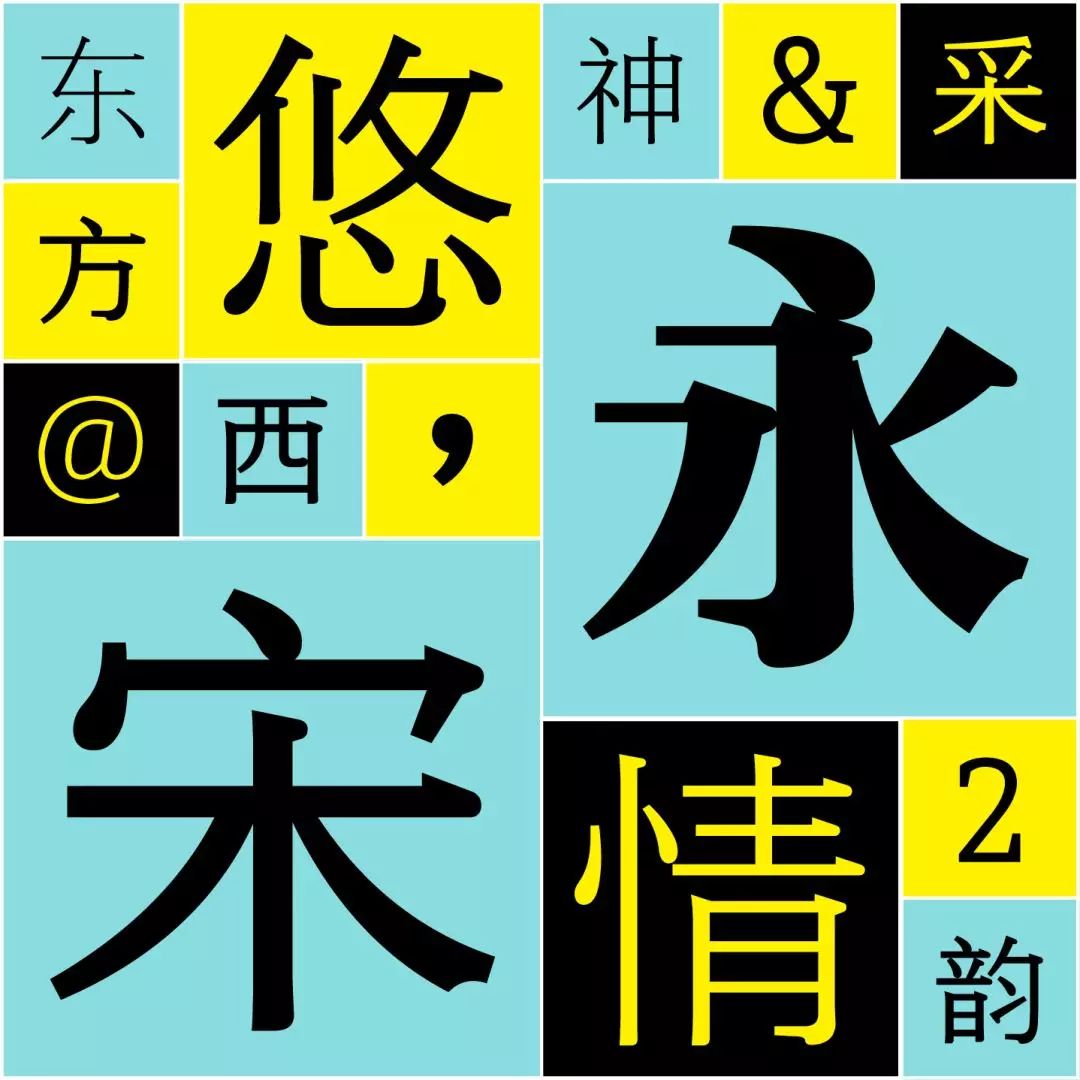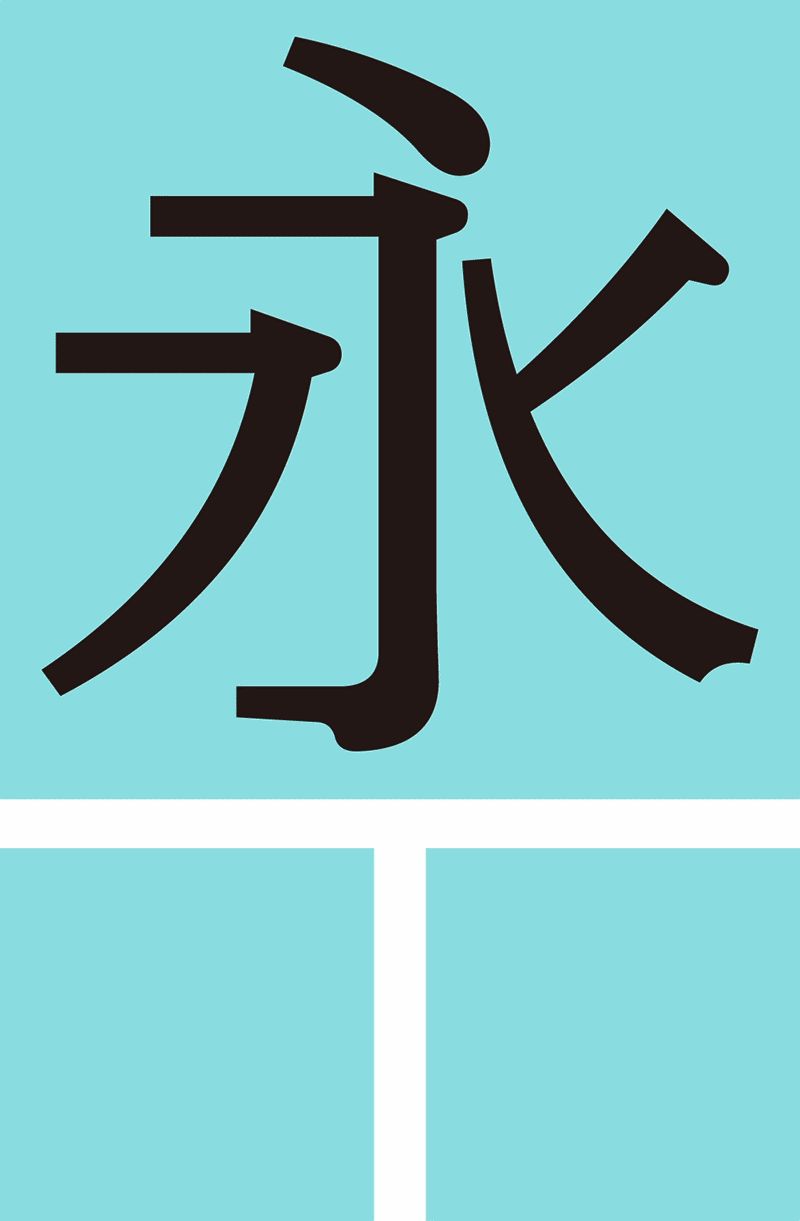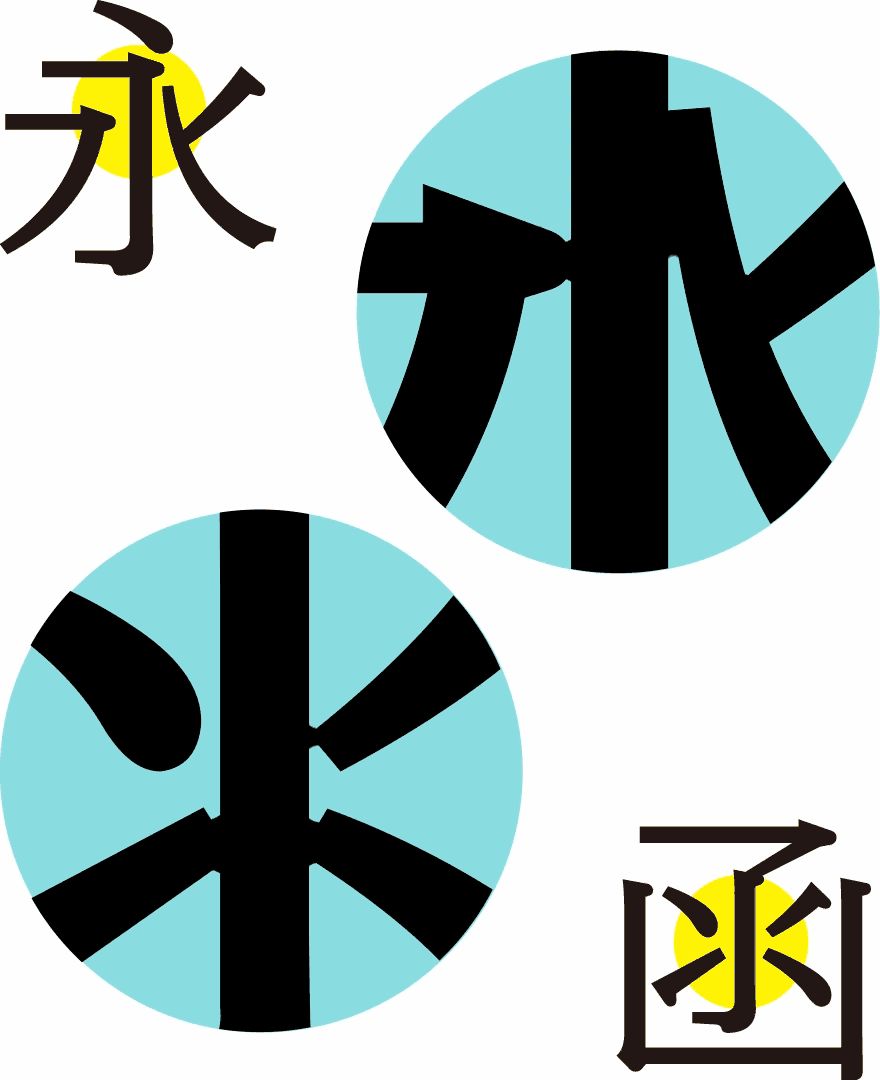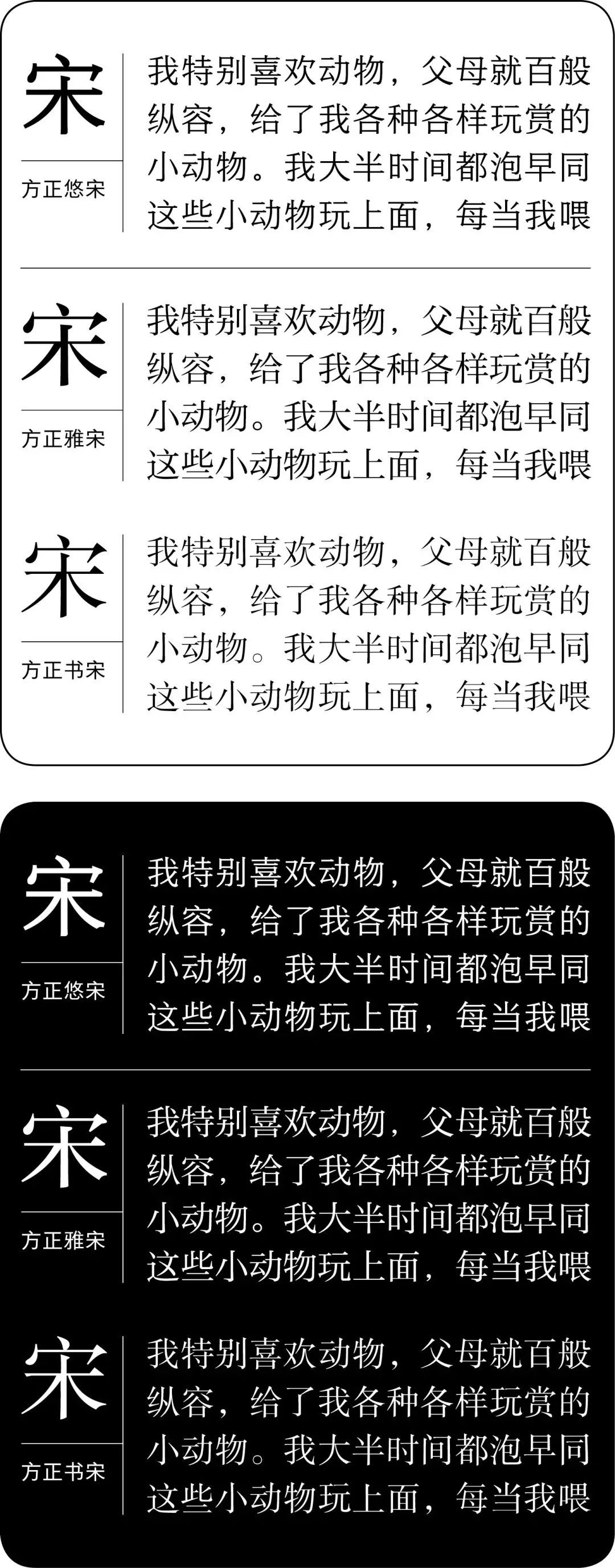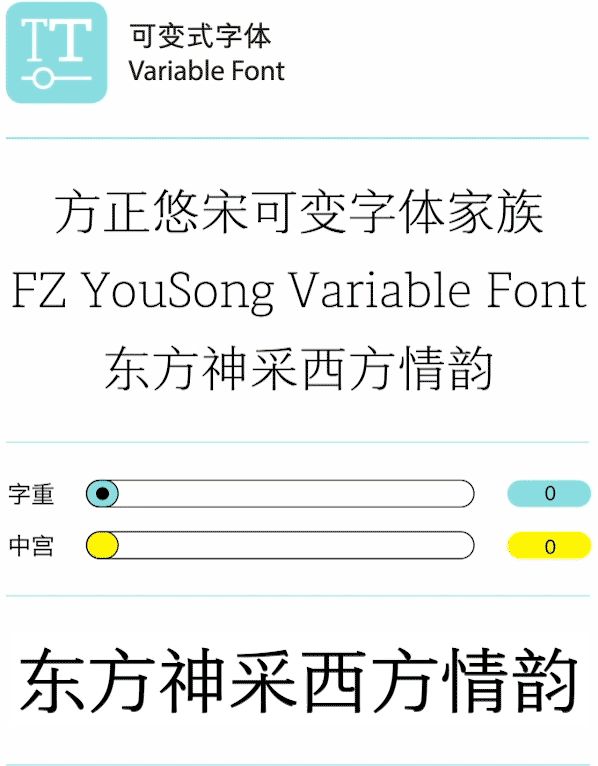
随着移动设备的广泛使用,屏幕已经成为了人们获取信息的主要途径。在这其中,大部分中文的内容则都交由黑体呈现。
市场上也偶尔出现过一些尝试使用宋体的应用。几年前,《澎湃新闻》上线之时选用了一款宋体,引发了一片惊诧。但波澜过后,鲜有其他成规模的屏幕宋体应用案例再次出现。除阅读惯性之外,再深究下去,我们似乎并未有一款真正为屏幕打造的宋体。
雅宋、书宋、标宋这些字体虽然很棒,但在设计之初,它们并未被考虑用于屏幕。同时,相较于黑体,宋体在屏幕上依然能够展现出令人惊叹的视觉风格。而且,宋体也与英文的衬线体类似,能够显著提高内容的可识别性,这在长篇阅读环境尤为重要。这也是在纸质书上我们看到的内容大多是宋体的原因。
《澎湃新闻》应用的内文界面
宋体历经雕版、活字、照排,逐渐形成了自己的风格。宋体适应着技术的发展,不断地变化和演进。然而,进入屏幕时代,宋体的进化曲线出现了一个垂直落体,早期屏幕分辨率并不适于表现宋体细腻的衬线和边角。
这直接导致我们当时在互联网上看到的中文内容,大部分都是由黑体承载的。长此以往,这种现象成为了一种通例,几乎成为了一种惯性。在这种惯性下,宋体就等于纸质内容,而黑体就天然等同于互联网内容。
那么,现在屏幕已经到达高清时代,技术壁垒已被碾碎。是时候来制作一款专为屏幕显示的宋体了。
在此之前,并没有一款专门为屏幕设计的宋体,要为屏幕设计宋体,几乎是在一个全新的领域从零开始,没有多少案例可循。不过,在屏幕上制造黑体,我们已有一些经验可以沿用。
那么,就从黑体开始吧,“悠黑”的骨架加上“宋体”的特征,这就是“方正悠宋”的基本形态。
为了提升屏幕阅读的效率,方正悠宋吸收了黑体的优点,它的基础是方正字库另一款饱受好评的黑体——方正悠黑。
宋体与黑体最大的区别,是笔画端点处的装饰角与笔画粗细的对比,方正悠宋将传统的倒三角样式改为直角三角形样式,使得字形与像素更为契合,提高字形在屏幕上显示的清晰度。在这样的设计理念下,方正悠宋的设计拥有了黑体的特性,也更加适合矩阵式的像素排列。
黑体因其横平竖直的特性,完全贴合像素边缘,传统宋体的边缘会虚化。悠宋融合了这两点,在拥有宋体特征的同时,也同黑体类似,尽力贴合了像素边缘。
宋体笔划末端的装饰角令人在阅读时能够有所喘息和停顿,我们其实比较熟悉,我们看的纸质长篇内容,无论是报纸还是书籍,其中的内容大多都是利用宋体呈现的。“方正悠宋”拥有这种特性,却使用得非常克制。
在方正悠宋的设计上,主创设计师仇寅刻意地减低了宋体的特征。
方正悠宋的笔形特征
六种宋体的折笔处笔形对比
对比这六款宋体,在折角处,悠宋主动将宋体的特征降低,这样做既保留了宋体能够给阅读带来停顿的优势,也让小字号下的显示更为精致。
纸面和屏幕呈现文字的原理各有不同。纸面就像月亮,反射光线而不自主发光。屏幕就像太阳,无论是通过背光面板(LCD),还是像素自发光(OLED),能够自主发光是其相较于纸面最主要的特征。那么,为其设计文字,也会因此不同。
笔划间适当离散,避免在屏幕显示时笔划粘连
方正悠宋专门为屏幕的特性进行了调整,在传统宋体的基础上适当放大中宫,笔画之间也进行了适当离散,这样避免了在屏幕显示过程中的笔画粘连与虚化。
适应屏幕自主发光特性,相对其他传统宋体,方正悠宋在不同显示环境中都拥有良好的阅读表现
在屏幕显示中,无论是白色还是黑色背景下,方正悠宋的阅读效果都更为舒适。而方正雅宋与方正书宋偶尔都有过挤或过松的问题,虽然它们也可显示于屏幕上,但“可用”和“适用”还是有所区别。
方正悠宋也拥有多种数字字体的新特性。第一,字重与中宫的无级可变特性令方正悠宋可以满足不同媒介情景的视觉需求;第二,精心调整的全套英文与标点系统让方正悠宋能够适应多种文本环境;第三,完整的字体家族增加了悠宋的视觉识别与信息层级的可塑性层级。
▼ 可变字体不仅能让设计师主动变化字重, 也能改变“中宫”的大小,令设计师可以在横竖两个方向和字面宽度各个方面对字体进行更为细微的调整。
▼ 方正悠宋拥有了专门为之适配的的英文与标点系统,不同字重的英文字体在与中文混排的时候也更加协调一致。
同时,方正字库也与 Typetogether 合作,为方正悠宋提供了一个与 Portada 英文组合的版本,以满足设计师在多语言环境下更为精细的排版需求。
▼ 极细到极粗,方正悠宋可以用来排印不同类型与层级的内容。今年,方正字库将正式推出方正悠宋的七款字重,将来会持续推出更多字重(总计十三款)。方正悠宋支持 GB2312-80 与 GB-18030-2000 标准,包含多达 27533 个汉字和1124个符号,可以满足不同尺寸便携屏幕的阅读要求。
方正悠宋家族同时适用于多种电子媒介,例如新闻媒体、电子阅读器以及 UI 设计等。与此同时,方正悠宋在传统纸质媒体上也同样拥有良好的设计表现。
屏幕阅读正持续在改变我们的阅读方式,从它诞生的那一天起就没有停歇。在西文新闻媒体已经开始大量使用衬线来统一自己品牌形象的今天,我们对于屏幕宋体的需求正在与日俱增。
在我们积累的大量优秀字体财富的基础上,以科技趋势为导向,总结优良经验,第一代中文屏显宋体——方正悠宋就此诞生。